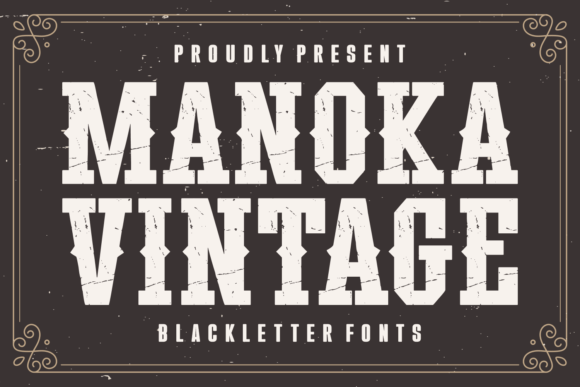
Manoka Vintage
Manoka Vintageのような高品質の素材をお探しの場合、このプレミアムパッケージはクリエイティブなプロジェクトに素晴らしい選択です。
精密に作られたManoka Vintageは、クリーンなベクター、滑らかなタイポグラフィ、そして安心のための商用ライセンスを提供します。
POD(オンデマンド印刷)製品、結婚式の招待状、またはソーシャルメディアのグラフィックを作成している場合でも、Manoka Vintageは理想的です。